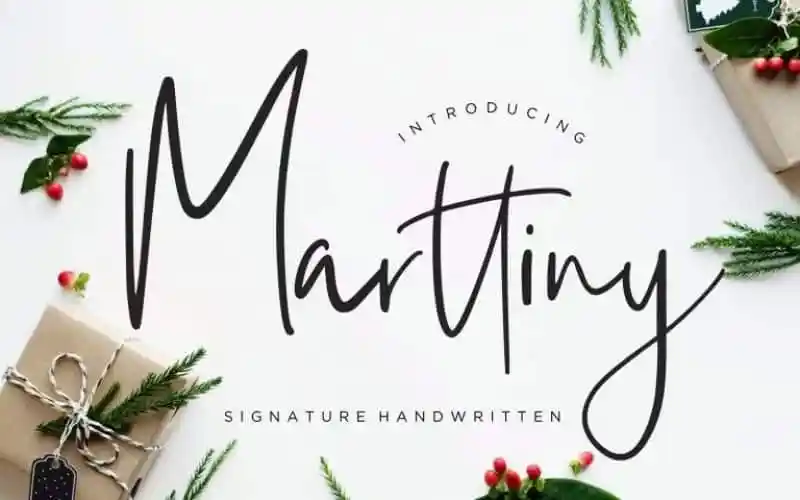
Marttiny Script Font – Download Grátis
Martiny Script Font é uma fonte de script elaborada cuidadosamente por a mão do designer Creatype Studio. Com seus caracteres impressionantes, essa font oferece aos designers um recurso versátil para projetos criativos como marcação e logotipos, designs de casamento, postagens nas redes sociais, anúncios, embalagem de produtos, designs de produto, selos, fotografia, marcas de água, convites e material de estaçãoária. Além disso, é ideal para qualquer projeto que deseje incorporar um toque de escrita a mão. Perfect para criar uma experiência única em sua próxima criação visual.